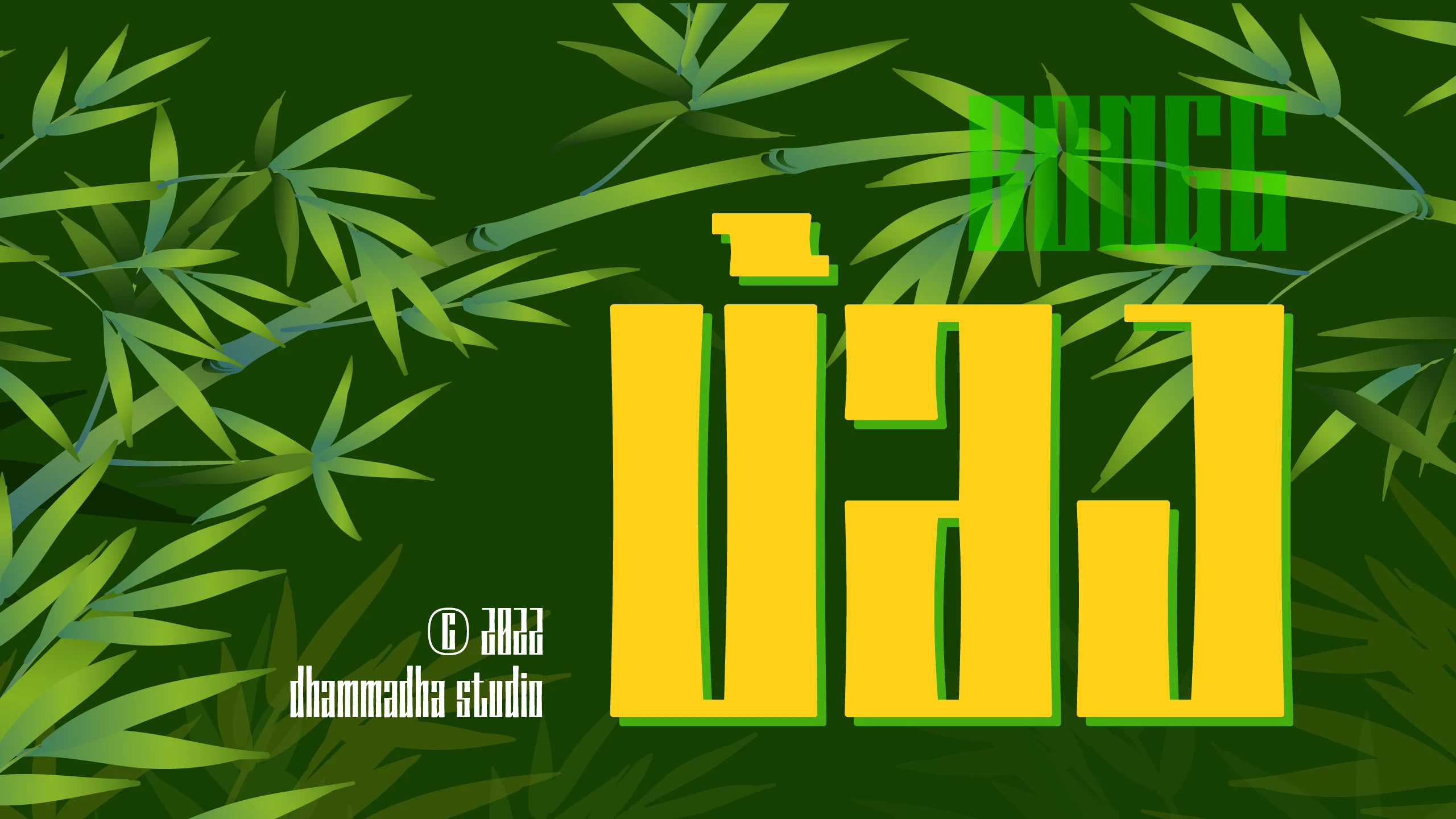
ชุดอักษรพาดหัว (Display Font) ทรงสูงที่ถูกออกแบบมาเพื่อทลายขีดจำกัดด้านพื้นที่ โดยมีจุดเด่นอยู่ที่โครงสร้างตัวอักษรที่ผอมสูงแต่หนักแน่น ช่วยให้คุณสื่อสารข้อความได้มากขึ้นในพื้นที่ที่จำกัด เอกลักษณ์ที่โดดเด่นที่สุดคือส่วนเว้าโค้งที่ได้รับแรงบันดาลใจจากรูปทรงของกระบอกไม้ไผ่ มอบมิติทางสายตาที่ดูมีความเคลื่อนไหวและลื่นไหลไปกับเนื้อความ ไม่หยุดนิ่งเหมือนฟอนต์ทรงสูงทั่วไป สร้างเสน่ห์ที่แปลกใหม่และน่าดึงดูดให้กับทุกการจัดวาง ด้วยบุคลิกที่ดูทันสมัยและมีจังหวะที่สนุกสนาน "บ้อง | BONGG" จึงเป็นตัวเลือกที่ยอดเยี่ยมสำหรับงานออกแบบที่ต้องการความโดดเด่นและเป็นระเบียบไปพร้อมๆ กัน ไม่ว่าจะเป็นการพาดหัวข่าวในนิตยสาร การออกแบบกราฟิกบนแพลตฟอร์มดิจิทัล หรือการสร้างอัตลักษณ์แบรนด์ที่ต้องการความเท่สไตล์ร่วมสมัย ฟอนต์ชุดนี้จะช่วยให้งานดีไซน์ของคุณดูมีพลัง มีเรื่องราว และบริหารจัดการพื้นที่บนชิ้นงานได้อย่างมีประสิทธิภาพสูงสุด พิเศษ !! ชุดฟอนต์ BONGG SIMPLE เมื่อต้องการใช้ในงานที่ต้องการความเป็นระเบียบมากขึ้น แถมฟรี !! เมื่อสั่งซื้อ BONGG FULL FAMILY